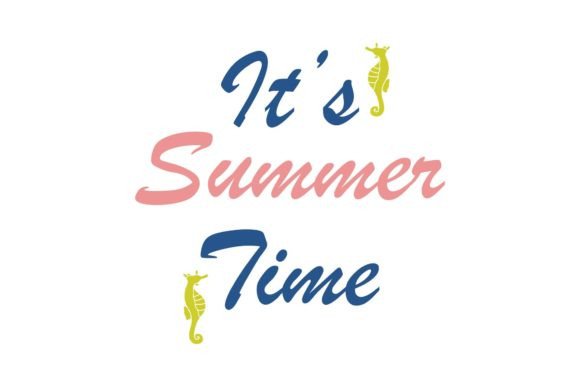
Quotes Summer Font
การค้นหาองค์ประกอบการออกแบบที่เหมาะสมอาจเป็นเรื่องท้าทาย แต่ Quotes Summer Font นำเสนอคอลเลกชันที่โดดเด่นซึ่งช่วยยกระดับงานของคุณได้ทันที
ไม่ว่าคุณจะสร้างผลิตภัณฑ์ POD (Print on Demand) คำเชิญงานแต่งงาน หรือกราฟิกโซเชียลมีเดีย Quotes Summer Font ก็เหมาะสมอย่างยิ่ง